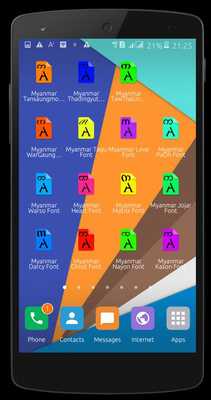
"Myanmar tansm Font" Root áááá¯ááá·á¹áá¼áá¹á¸ á»ááá¹áá¬á á¬áá¯á¶á¸á¡áá½áá á¹áá¯á»áá á¹áá«ááá¹ááá¯áá¹á¸áá½á¬á»ááá¹áá¬á á¬áá¯á¶á¸á¡áá½áá¯á¶á¸ááºáá¹áá°ááºá¬á¸á¡áá¼áá¹
Myanmar Tansaungmone ááá¯áá²á·á á¬áá¯á¶á¸á¡ááá¹á¸á±áá¸áá á¹áá¯áá«á
á¡ááá¹á¸ááá¹á¸áá«áá²á·á á¬áá¯á¶á¸áá¯á¶á á¶á±áá¸áá«á
"Myanmar Tansaungmone" Font is Beautiful Myanmar Zawgyi Font Style!